23 Thiết kế website với Serif typefaces
Hiện nay thiết kế website càng ngày càng phát triển, thiết kế không chỉ cần đầy đủ các chức năng hay hình ảnh, hiệu ứng đẹp mà kiểu chữ cũng là một yếu tố rất quan trọng cấu thành nên thiết kế web.
Các Serif typefaces (kiểu chữ có chân) không phổ biến ở các trang web, nhưng văn bản sans-serif (kiểu chữ không chân) có vẻ như chiếm ưu thế trong ngành công nghiệp thiết kế web, mặc dù các công nghệ hiện đại cung cấp một thư viện lớn các phông chữ của tất cả các kiểu chữ.
Kiểu chữ không chân được nhận biết bởi những hình dạng chữ đơn giản hơn với những nét gần như đều nhau, thiếu những dấu hiệu tương phản, sử dụng các hình dạng hình học (chữ nhật, tròn, ovan…) trong thiet ke web. Sự tương phản thấp, không chân hình thành hầu hết những mặt chữ sans serif và khiến chúng thiếu đi sự liền mạch để đọc như các chữ có chân. Chúng tốt cho một câu, ổn với một đoạn (paragraph), nhưng khó để sử dụng tốt khi dùng cho chữ trên một cuốn sách.
Tuy nhiên, khi bạn tìm thấy những ví dụ về sử dụng Serif typefaces trong thiết kế web bạn sẽ thật sự ấn tượng. Dựa trên những yếu tố tiêu chuẩn của nét và tính cách bởi sự tương phản mạnh, các chân trở nên sắc nét hơn tạo nên mới vẻ đẹp mới cho những đoạn văn bạn. Sau đây là 25 mẫu thiết kế trang web với Serif typefaces, những trang web này sử dụng phông chữ serif sang trọng để tạo ra thiết kế phong cách và tinh xảo.
01. Rokkan
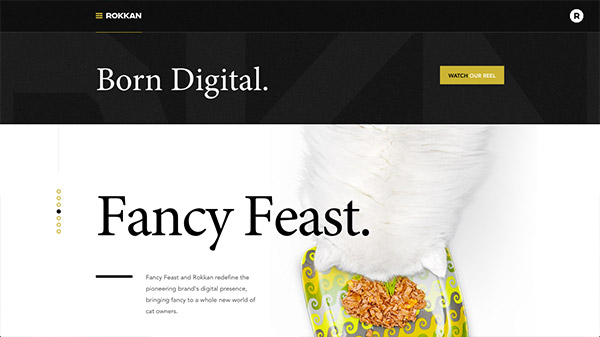
02. Tyler Copeland
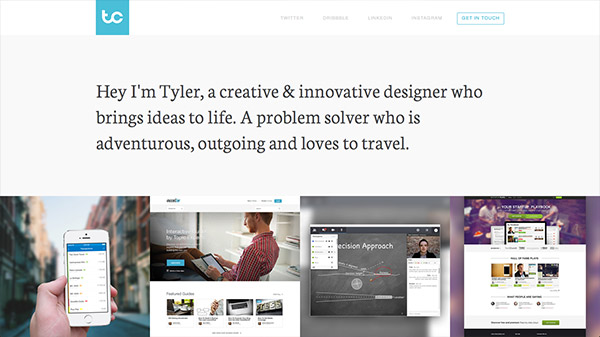
03. Dragone
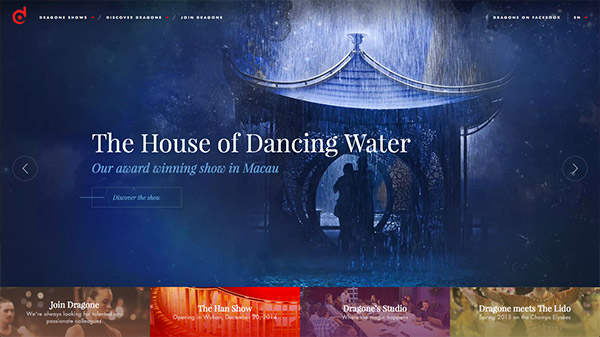
04. Vesper Hotel Noordwijk
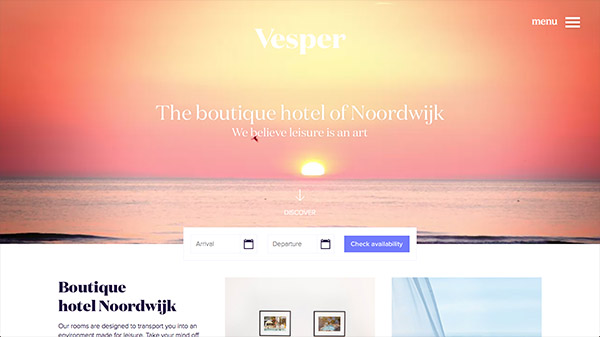
05. Solo
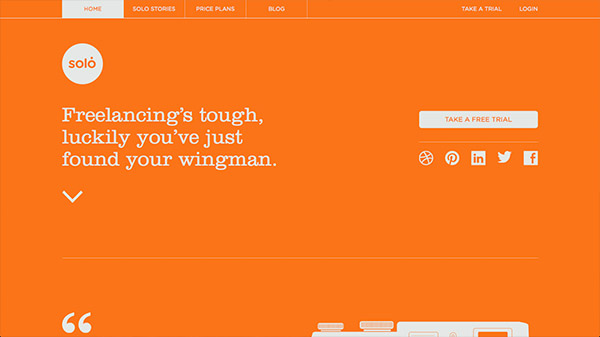
06. Q Ideas
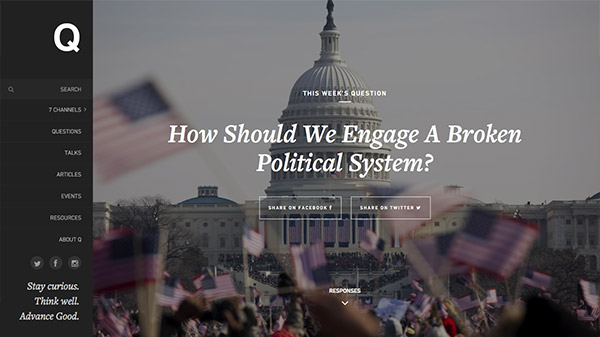
07. Studio MPLS
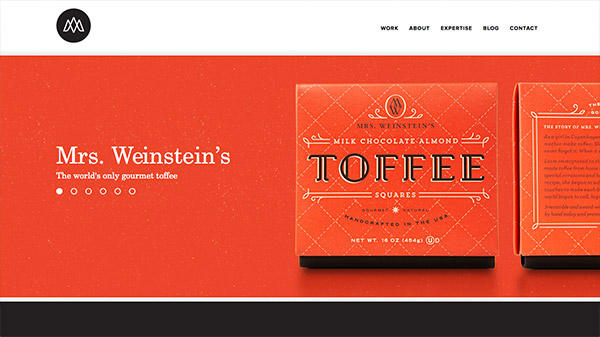
08. Essence
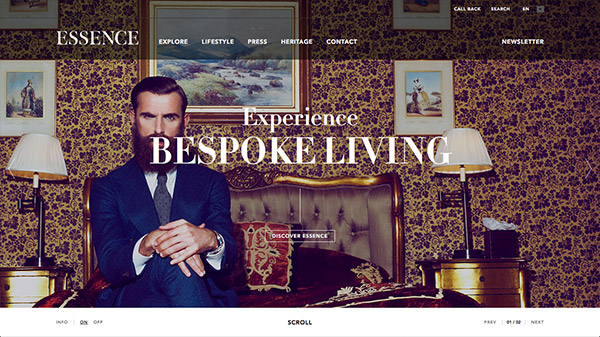
09. Chattanooga Renaissance Fund
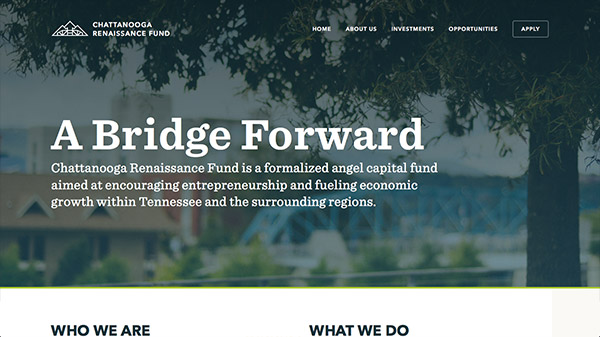
10. Rook
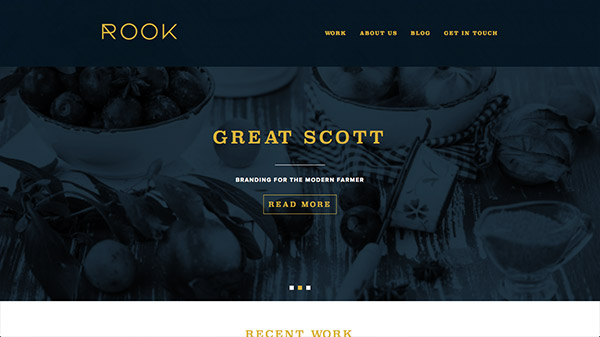
11. Simpleblend
12. PRPL
13. Webstock 2015
14. Aria Studio
15. Wondersauce
16. Kin HR
17. Cher Ami
18. Future Father
19. Generation Press
20. OKREAL
21. Sweden Unlimited
22. Instrument
23. The Fernway